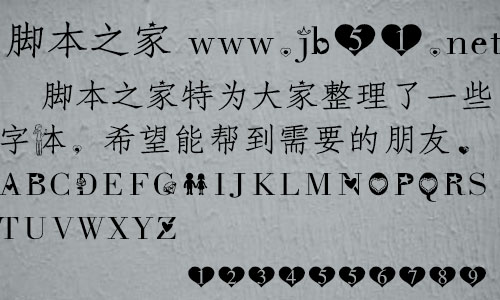
字體管家白色戀人是一款不錯的藝術(shù)字體,由Aa字庫出品,字體筆觸纖細,字形端正,以心形卡通圖案、玫瑰卡通圖案以及一對情侶卡通圖案作為點綴,具有很好的視覺感,適合應(yīng)用于藝術(shù)設(shè)計、平面宣傳設(shè)計、網(wǎng)頁設(shè)計,書法字帖等領(lǐng)域,需要的朋友可以前來本站下載。